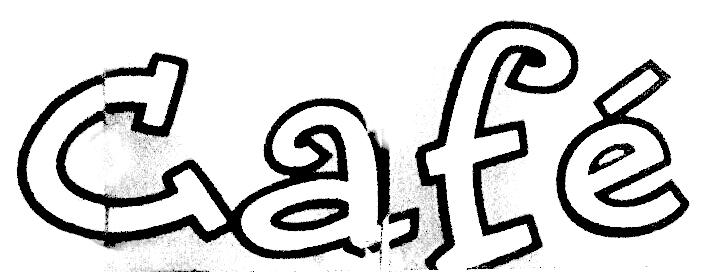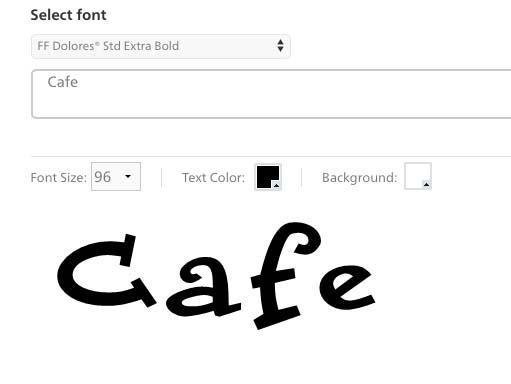
Schriftart einer Kaffeebar gesucht
ich nehme für einen Kunden die Umgestaltung seiner Kaffeebars vor. Habe hierzu anbei nen Ausschnitt von nem Fax zur Orientierung.  Die Schrift ist recht charakteristisch und kommt mir bekannt vor, dennoch finde ich sie seit stundenlangem Suchen nicht, bin aber gezwungen, diesen Font wieder zu benutzen. Vll hat jemand von Euch nen Geistesblitz?
Recht verzweifelt werde ich mich sonst langsam auf einen langen Umweg zur Findung machen.